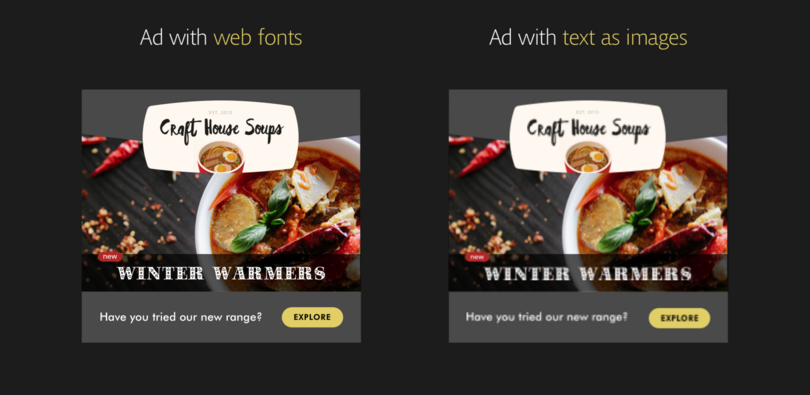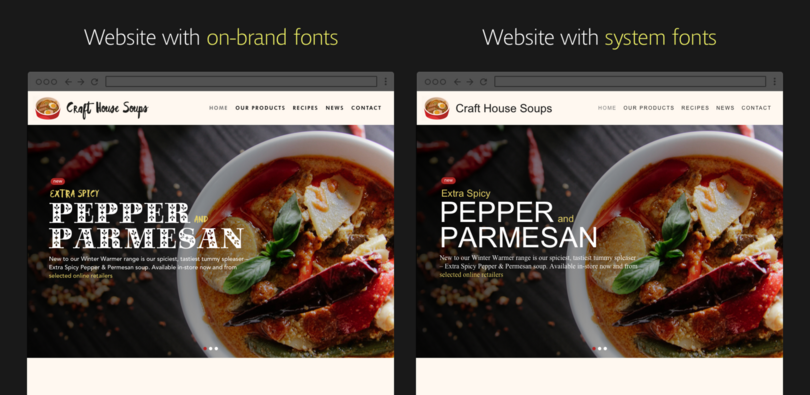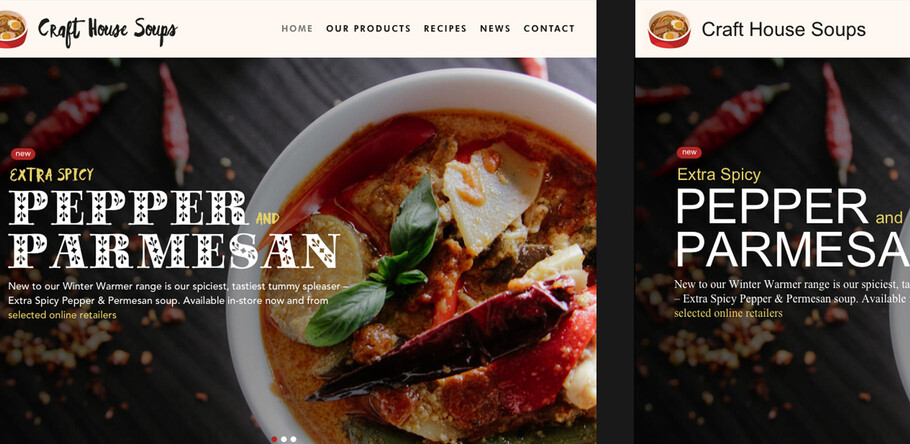
Die Markenidentität wahren: plattformsichere Fonts
Hat man sich auf eine bestimmte Schrift für die eigene Marke festgelegt, dann geht man davon aus, dass diese wie selbstverständlich funktionieren wird – egal wofür man sie verwenden möchte. Die Realität sieht jedoch anders aus. Damit der visuelle Auftritt einer Marke keinen Schaden nimmt, sollten Unternehmen einige Dinge beachten.
Schriften sind Software, die für unterschiedliche Anwendungsfälle entworfen werden. Auf dem Computer bereits vorinstalliert sind eine Anzahl von Desktop-Fonts, sogenannte Systemschriften. Sie können bei Printprojekten, in JPEGs, GIFs oder anderen Bilddateien eingesetzt werden. Sie können mit Einschränkungen auch auf Webseiten verwendet werden. Dazu später mehr.
Im Gegensatz zu Systemschriften werden Web-Fonts bei Bedarf von einem Server heruntergeladen und kommen auf Webseiten und in Online-Anzeigen zum Einsatz – mit der entsprechenden Lizenz. Web-Fonts zeichnen sich insbesondere durch ihr responsives Design und die Anpassungsfähigkeit für die Verwendung auf mobilen Geräten aus.
Auswirkungen auf die Marke
Für ein einheitliches Markenbild über alle Kunden-Touchpoints hinweg ist es entscheidend, die richtige Schrift am richtigen Ort zu verwenden. Kunden, vor allem die junge, technikaffine Zielgruppe, erwarten, dass eine Marke auf mehreren Plattformen verfügbar ist und sie problemlos und ganz nach ihrem Bedarf damit interagieren können. Laut Angaben von Google wechseln heute 65 Prozent der User während der Internetnutzung auf ein zweites Gerät.
Ist dann nicht überall dieselbe Schrift zu sehen, kann das Auswirkungen auf den visuellen Auftritt der Marke haben und widersprüchlich und inkonsequent wirken. Das beeinträchtigt nicht nur das Vertrauen der Kunden in das Branding, sondern stellt auch das Team vor schwierige Herausforderungen. Die Gründe dafür sind vielfältig:
Verwendung von Systemschriften
Das Problem bei Systemschriften: Man geht davon aus, dass jeder Kunde die Schrift auf seinem Computer installiert hat. Doch nicht jedes System – sei es ein Mac, ein Windows-PC oder ein Smartphone – verfügt über die gleichen Fonts.
Sollte Ihre Corporate-Schrift auf dem Gerät des Kunden nicht verfügbar sein, so verwendet die Webseite eine Standardschrift, wie dieses Beispiel zeigt:
Die linke Webseite verwendet Web-Fonts, die für eine einheitliche Markenidentität in allen Anwendungsfällen sorgen. Die Webseite rechts wurde mit Systemschriften erstellt und verwendet eine beliebige Standardschrift.
Nicht immer kann diese Standardschrift im Code vorgegeben werden. Dann entspricht das Anwendungserlebnis des Kunden möglicherweise nicht dem Anspruch des Unternehmens und wird der Marke nicht gerecht. Darüber hinaus verfügen mobile Endgeräte häufig über kleinere Font-Bibliotheken. Somit ist die Wahrscheinlichkeit, dass User nur eine Standardschrift zu sehen bekommen, hier noch höher. Da laut ComScore bereits 65 Prozent der Onlinemedien über mobile Geräte genutzt werden – Tendenz steigend – müssten sich somit viele Kunden mit einem mäßigen Anwendungserlebnis zufrieden geben.
Unscharfe Online-Anzeigen
Mit der entsprechenden Lizenz für Online-Anzeigen präsentieren Web-Fonts den Text in einer klaren, gestochen scharfen Schrift, die Ihre Marke optimal widerspiegelt. Web-Fonts lassen sich auch für dynamische Inhalte verwenden, um Texte zu individualisieren und kundenspezifisch anzupassen. Des Weiteren stellen Web-Fonts sicher, dass Ihre Anzeige und damit Ihre Marke auf jedem Gerät einheitlich dargestellt werden.
Die Alternative dazu ist die Einbettung des Textes (als Pixel) in eine JPEG-, PNG- oder GIF-Datei zusammen mit dem im Layout verwendeten Bildmaterial. Auf diese Art gelingt jedoch nie eine so scharfe und klare Textdarstellung wie mit Web-Fonts – das gilt insbesondere für hochauflösende Bildschirme. Auch kundenspezifische oder Größenanpassungen für unterschiedliche Bildschirme sind mit Pixeln nicht möglich.
Links: Durch die Verwendung von Web-Fonts ist der Text gestochen scharf und klar. Rechts: Die Einbettung des Textes in ein Bild beeinträchtigt die Qualität der Anzeige.
Inkonsistentes Marke in HTML-E-Mails
In der Regel bestehen E-Mails aus Bildern und Text, wobei der Text möglicherweise Ihren Corporate-Font verwendet. Ist das nicht der Fall, so wird der Text normalerweise in einer Standardschrift wiedergegeben oder in ein Bild eingebettet, das Kunden eventuell nicht herunterladen.
Mit der Verwendung von Web-Fonts lassen sich solche Probleme von vornherein vermeiden. Zudem bieten sie die Möglichkeit, Inhalte zu personalisieren. Viele, wenn auch nicht alle Mail-Clients unterstützen Web-Fonts, so zum Beispiel das Mailprogramm von Apple oder das eigene Programm verschiedener Android-Versionen. Für den Fall, dass Web-Fonts nicht unterstützt werden, können Marken jedoch zumindest alternative Schriften selbst bestimmen.
Genauso wie auf Webseiten sorgt die Verwendung von markenspezifischen Schriften in HTML-E-Mails für einen einheitlichen Markenauftritt.
Die zunehmende Nutzung mobiler Endgeräte wird voraussichtlich dazu führen, dass Web-Fonts in Zukunft immer häufiger in E-Mails Verwendung finden. Marketingmitarbeiter, die schon heute auf Web-Fonts setzen, können ihrer Brand nicht nur einen Wettbewerbsvorteil verschaffen, sondern bieten Kunden mit unterstützenden Mail-Clients zudem ein deutlich besseres Nutzererlebnis.
Lizenzpakete sind häufig die beste Lösung. Denn erweiterte Lizenzen stellen sicher, dass Ihre Fonts immer und überall ordnungsgemäß verwendet werden und minimieren das Risiko, dass Schriften in falsche Hände geraten. Das Ergebnis: Die Fonts funktionieren genauso, wie Sie es von ihnen erwarten, und Ihre Marke präsentiert sich mit einem einem einheitlichen visuellen Auftritt – während Ihr Team sich ganz auf seine Arbeit konzentrieren kann.